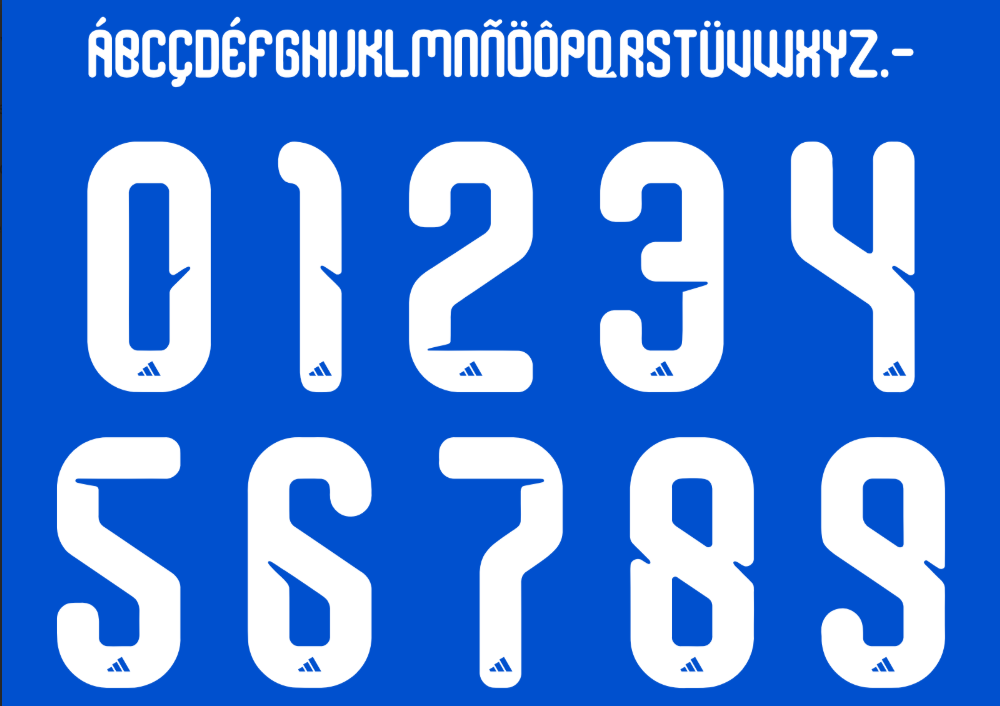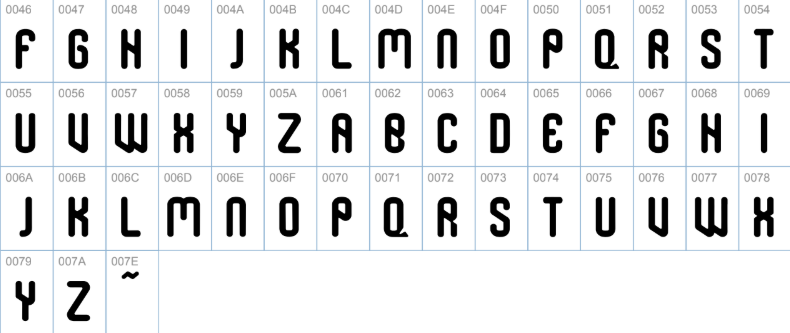
A temporada 2026/27 marca mais um capítulo na gloriosa história da Universidad de Chile. A parceria duradoura com a Adidas continua a entregar uniformes que misturam a tradição do “Romántico Viajero” com a tecnologia de ponta da marca alemã. Para este ciclo, o design aposta em uma estética limpa, valorizando o azul profundo que é a alma do clube.
Um dos pontos altos do novo kit é, sem dúvida, a tipografia. Fontes de camisas de futebol não servem apenas para identificação; elas compõem a personalidade do uniforme. A fonte utilizada nesta temporada reflete modernidade e movimento, harmonizando perfeitamente com as três listras da Adidas e o icônico “U” no peito.
Se você é designer, editor de PES/eFootball ou criador de conteúdo esportivo, ter acesso a essa fonte é essencial para garantir o realismo e a qualidade profissional dos seus projetos. Abaixo, apresentamos a fonte Universidad de Chile 2026 – 27, uma recriação fiel inspirada na tipografia utilizada pelos jogadores em campo.
Estilo visual da tipografia
A tipografia desenvolvida para a Universidad de Chile na temporada 2026/27 segue a linguagem visual global da Adidas, mas com adaptações que garantem leitura rápida e estética esportiva.
- Design e Geometria: A fonte apresenta um estilo sans-serif (sem serifa) condensado, com bordas levemente arredondadas ou cortes diagonais (dependendo da variação exata da temporada), transmitindo uma sensação de velocidade e dinamismo.
- Aplicação no Uniforme: No uniforme titular (Home Kit), a numeração e os nomes são aplicados na cor branca, criando um contraste clássico e legível sobre o azul royal. No uniforme reserva (Away Kit), geralmente branco ou creme, a fonte assume a cor azul ou vermelha, mantendo a identidade do clube.
- Personalidade: É uma fonte que equilibra o peso robusto necessário para a visibilidade em campo com a elegância exigida por um gigante do futebol sul-americano. Ela evita excessos decorativos, focando na funcionalidade e no estilo “performance”.